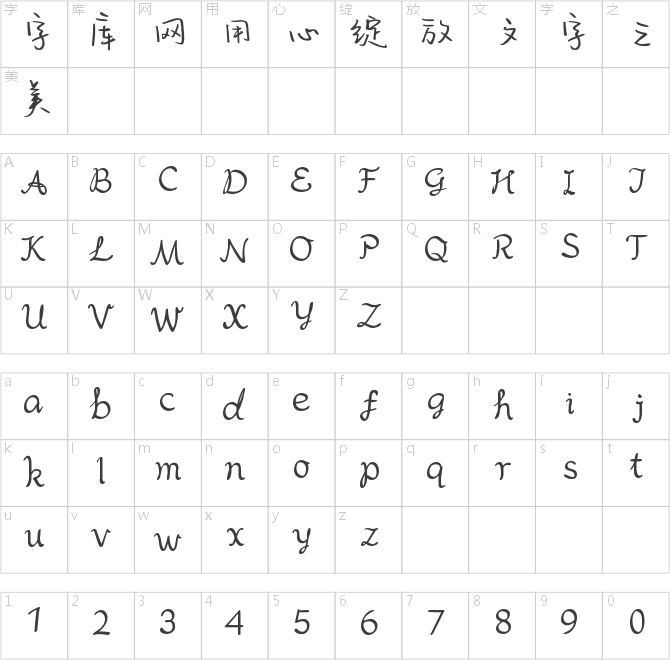
情話說(shuō)給風(fēng)聽(tīng)
情話說(shuō)給風(fēng)聽(tīng)字體字庫(kù)是一款讓人賞心悅目、百看不厭的中文字體,適合各類(lèi)廣告和產(chǎn)品包裝設(shè)計(jì)應(yīng)用,字體大小3.07MB,格式為ttf字體,上傳用戶(hù)是文道字庫(kù),作者/版權(quán)方為文道